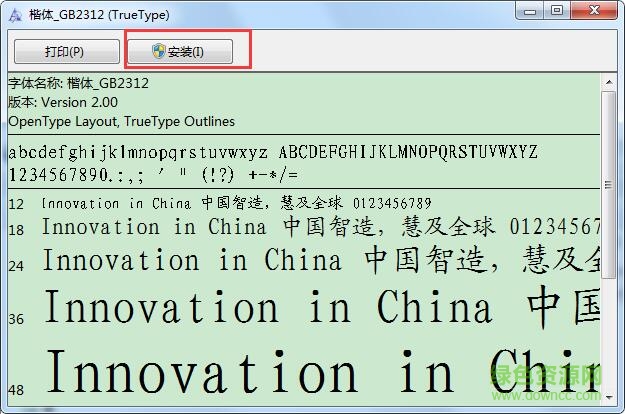
館閣體是一款類似于小楷字體的毛筆書(shū)法,是音古代科舉制作而形成的一款獨(dú)特字體,注重格式和構(gòu)造,有著干練有力運(yùn)筆流暢之美,喜歡的朋友不妨來(lái)綠色資源網(wǎng)體驗(yàn)哦!
館閣體,是指因科舉制度而形成考場(chǎng)通用字體,以烏黑、方正、光沼、等大為特點(diǎn)。
明代稱“臺(tái)閣體”,清代改稱“館閣體”。明永樂(lè)時(shí),翰林院侍講學(xué)士沈度,其書(shū)法風(fēng)格秀潤(rùn)華美,正雅圓融,深受成祖朱棣賞識(shí),因而名重朝野,乃至片紙千金,上有好,下必甚焉,士子爭(zhēng)相仿效,遂成標(biāo)準(zhǔn)書(shū)體。
館閣體作為官方使用的一種書(shū)體,強(qiáng)調(diào)共性,強(qiáng)調(diào)規(guī)范,本是無(wú)可厚非的,以批評(píng)館閣體缺乏個(gè)性為由而借機(jī)兜售今人丑怪的書(shū)風(fēng),顯然暴露了不健康的心理;而從欣賞美的角度出發(fā),缺乏個(gè)性的東西也是不完美的。
當(dāng)今的楷書(shū)創(chuàng)作,最大的弊端在于為楷書(shū)而楷書(shū),時(shí)刻注意著標(biāo)準(zhǔn),形成慣性。拿最普遍的顏真卿楷書(shū)來(lái)說(shuō),顏體的大概規(guī)律是橫細(xì)豎粗,但是顏氏不同時(shí)期的字有不同的變化,同樣一個(gè)帖子中也并非完全遵照這個(gè)規(guī)律。就好像哲學(xué)中常提到的一個(gè)命題,你可以說(shuō)表是圓的,但不能說(shuō)所有的圓形都是表。然而在書(shū)法中,落實(shí)到教學(xué)和創(chuàng)作,卻往往死守著這樣的概論不得變通。這恰恰違反了楷體字誕生之初那種“越名教而任自然”的氣質(zhì),將它陷于了僵化的體制中,以至于窒息而死。最好的例證就是“館閣體”的僵化形態(tài)。所以,鄭燮曾有詩(shī)云:“蠅頭小楷太停勻,長(zhǎng)恐工書(shū)損性靈?!边@話表達(dá)了那個(gè)時(shí)代的士人的普遍心態(tài)。鄭燮在早期為參加科舉考試而專攻工整楷書(shū),而在考中進(jìn)士后就從自己性情出發(fā)來(lái)表現(xiàn)個(gè)性了。如其《城隍廟碑記》楷書(shū),參合唐楷、魏碑,打破方嚴(yán)而出現(xiàn)欹側(cè)和伸展撇捺,真正給楷書(shū)注入了新鮮血液,在楷書(shū)史上取得了成功。
館閣體已轉(zhuǎn)化為現(xiàn)在常見(jiàn)的楷體GB2312,望周知!